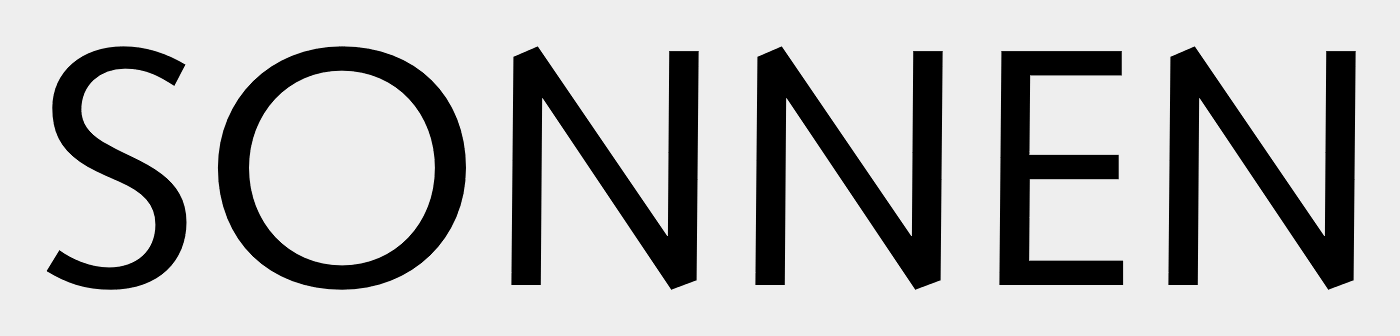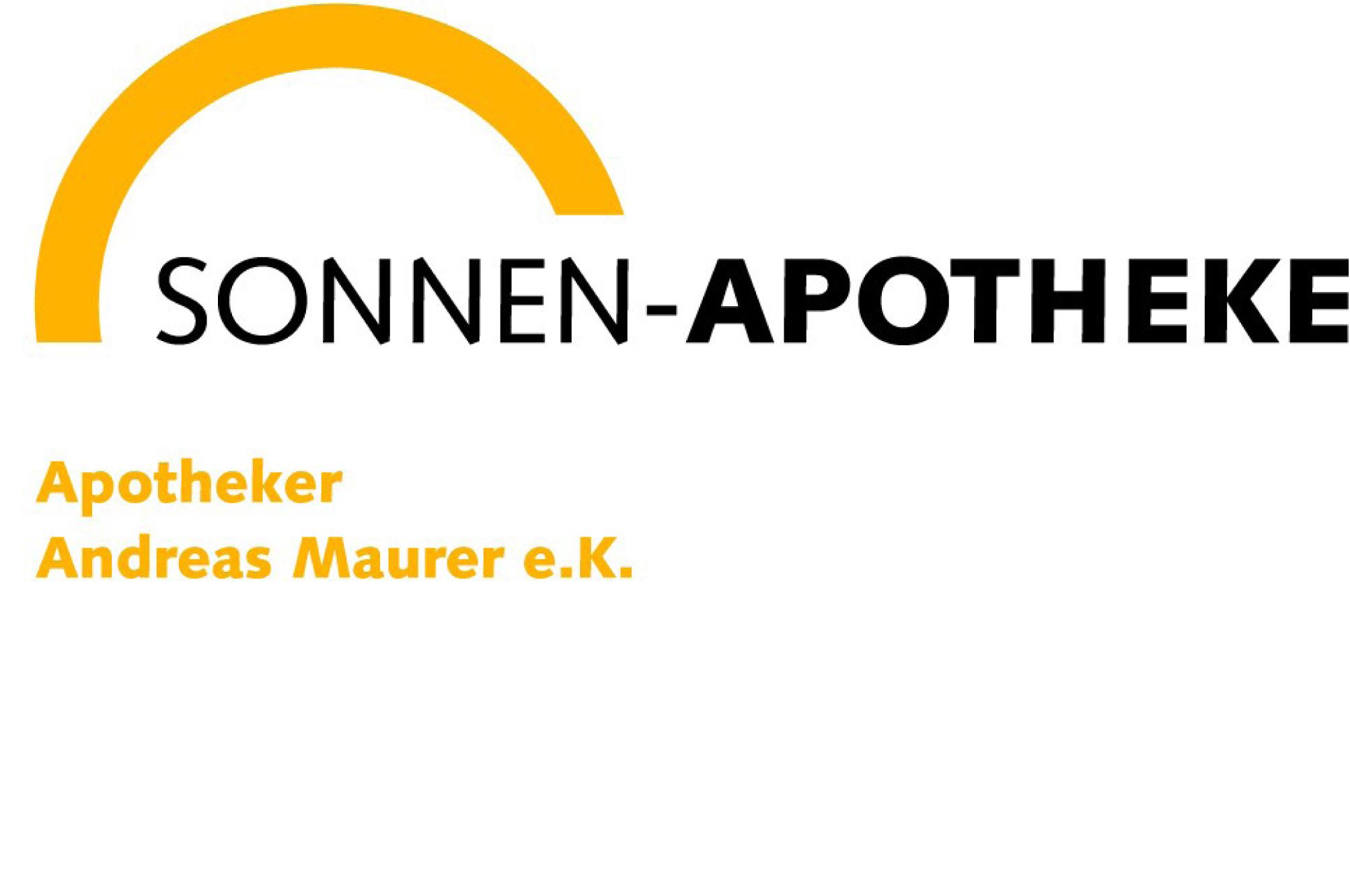
Schrift von Sonnen-Apotheke
ich verzweifle gerade an der Suche der Schrift (siehe angehängte Datei).
Sieht alles ganz klar aus, aber dann entdeckt man die abgeschrägten Spitzen am Buchstaben "N" im Wort "SONNEN".
Kennt einer von euch diesen Font? Wenn man die beiden "O"s vergleicht von "SONNEN" und "APOTHEKE" bin ich mir fast sicher, dass hier zwei unterschiedliche Schriften zum Einsatz kommen.
Könnte aber auch
– CG Symphony Regular von Monotype
– Humanist 531 BT von ParaType
sein.
Family: Syntax BQ (Roman)
FontSet: Berthold / (Commercial)
siehe erster Eintrag oben rechts. welches tool? siehe fenster oben mitte